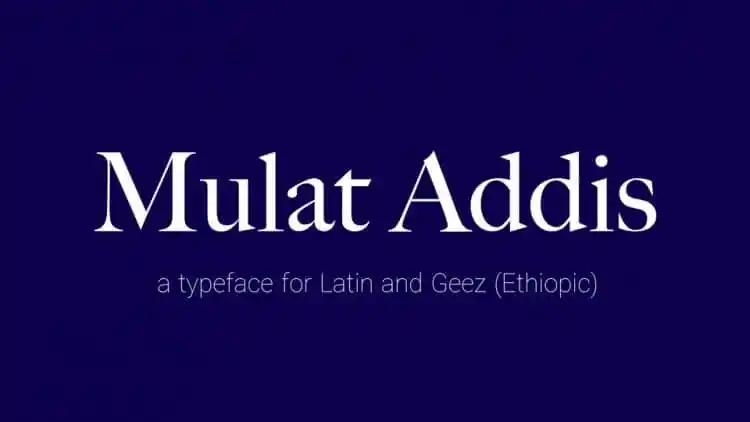
A Mulat Addis Sans Serif é uma fonte serílica que captura a elegância simples e formal dos estilos serifados mais tradicionais. Criada pelo designer Fasil Fikreab, essa fonte oferece um equilíbrio entre simplicidade e sofisticação, combinando facilidade de leitura com uma aparência atraente e moderna. Ideal para aplicações que valorizam tanto a elegância clássica quanto a funcionalidade moderna, ela é perfeita para designers buscando um contraste agradável entre linhas serílicas e formas limpas. Além disso, a Mulat Addis Sans Serif é uma fonte multilíngue que suporta os scripts latinos e gêez. O designer Fasil Fikreab tem o cuidado de adaptar essa característica ao design da fonte, introduzindo capitalização para os idiomas baseados no script gêez (ethiopiano) em aplicativos compatíveis com ligaduras e recursos OpenType. Para aqueles que buscam um estilo serílico contemporâneo, sem abrir mão de uma aparência elegante e formal, a Mulat Addis Sans Serif é uma excelente escolha para criar designs multifacetados e impecáveis.